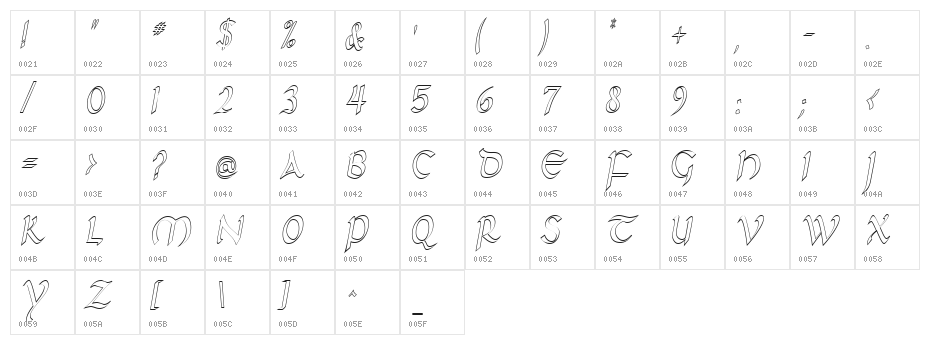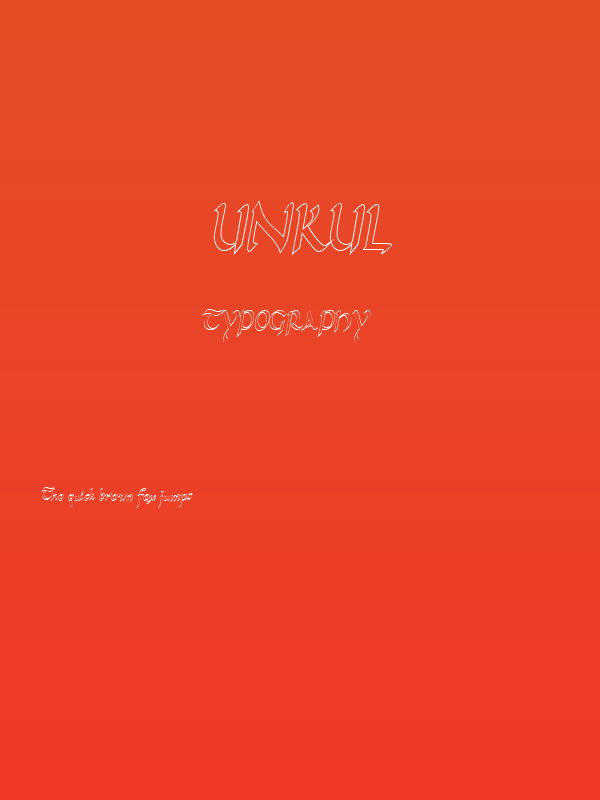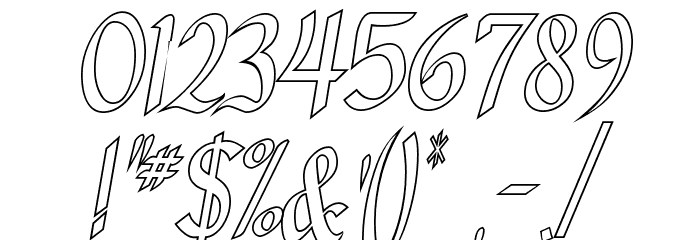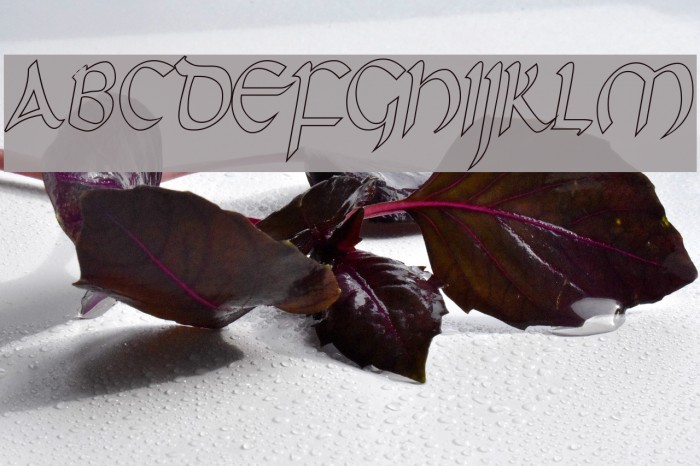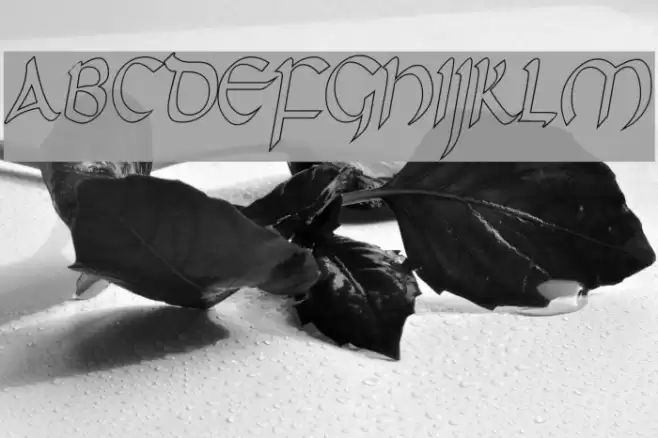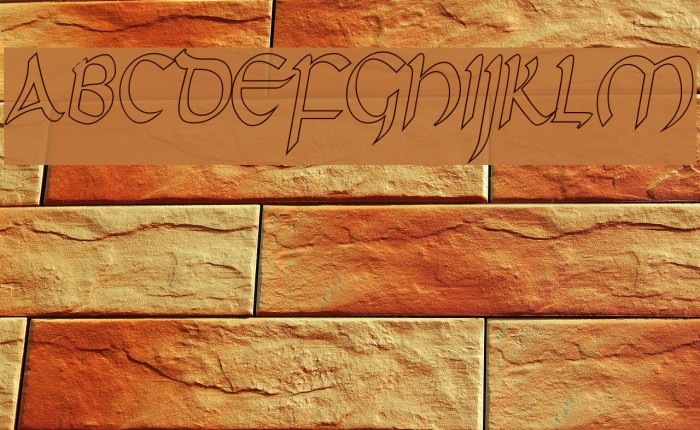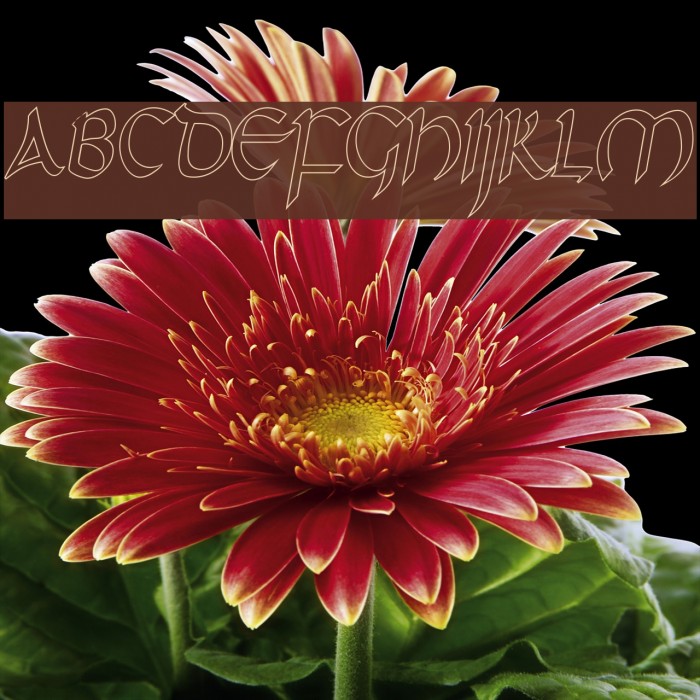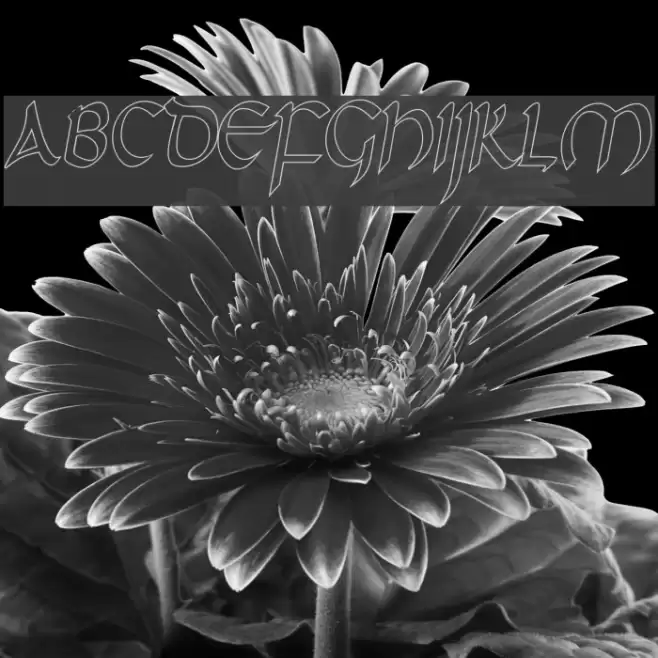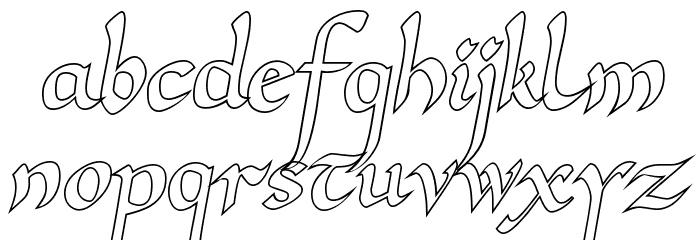
Unkul Font
✎ Outline
| Proiecte propuse | Ideal for branding, logos, invitations, and creative design projects that require a touch of elegance and modernity. |